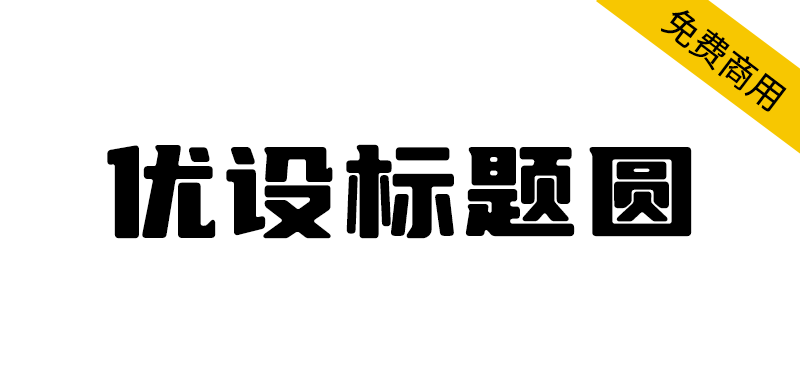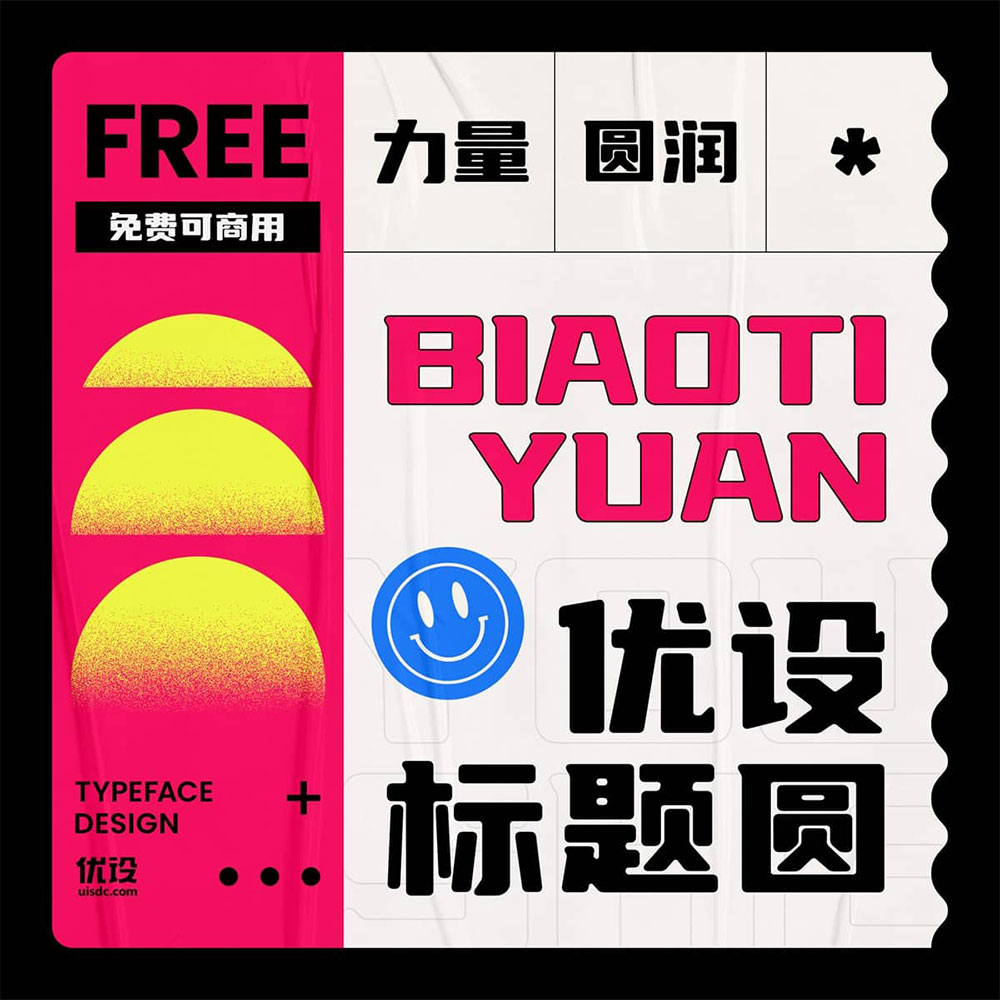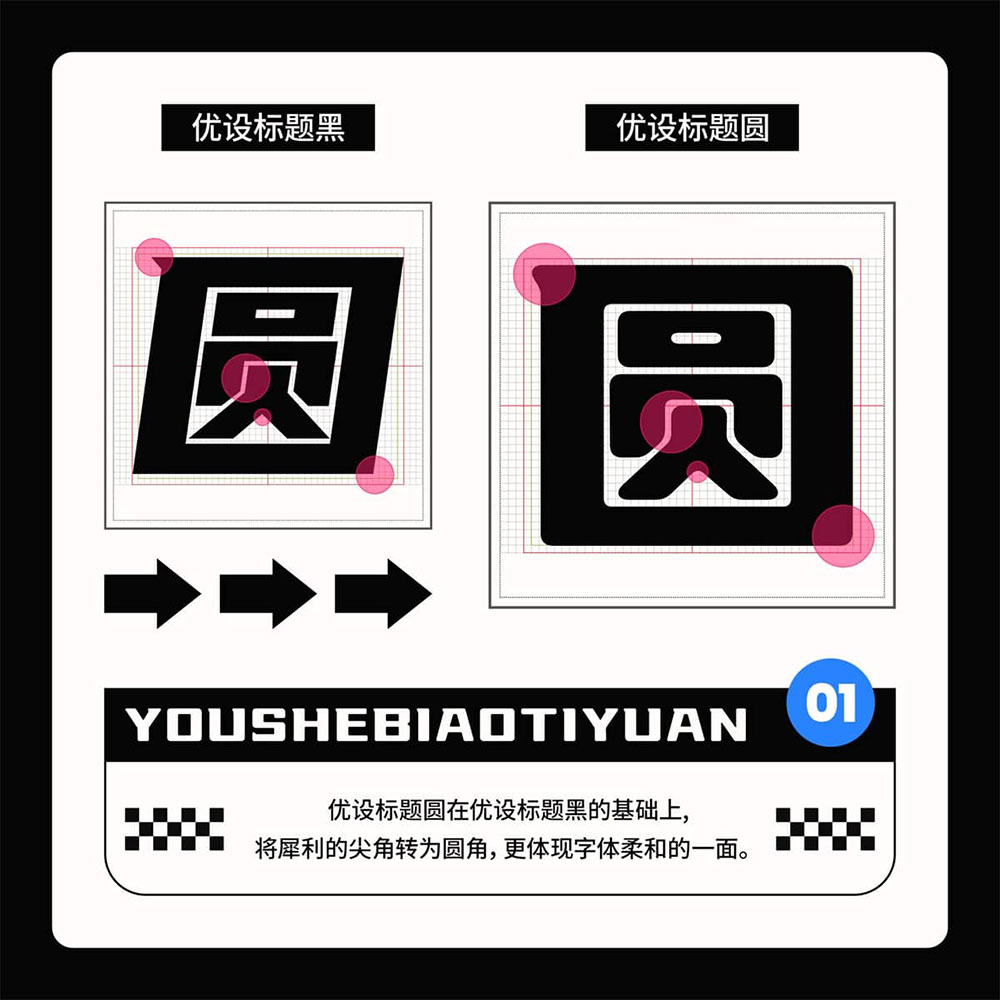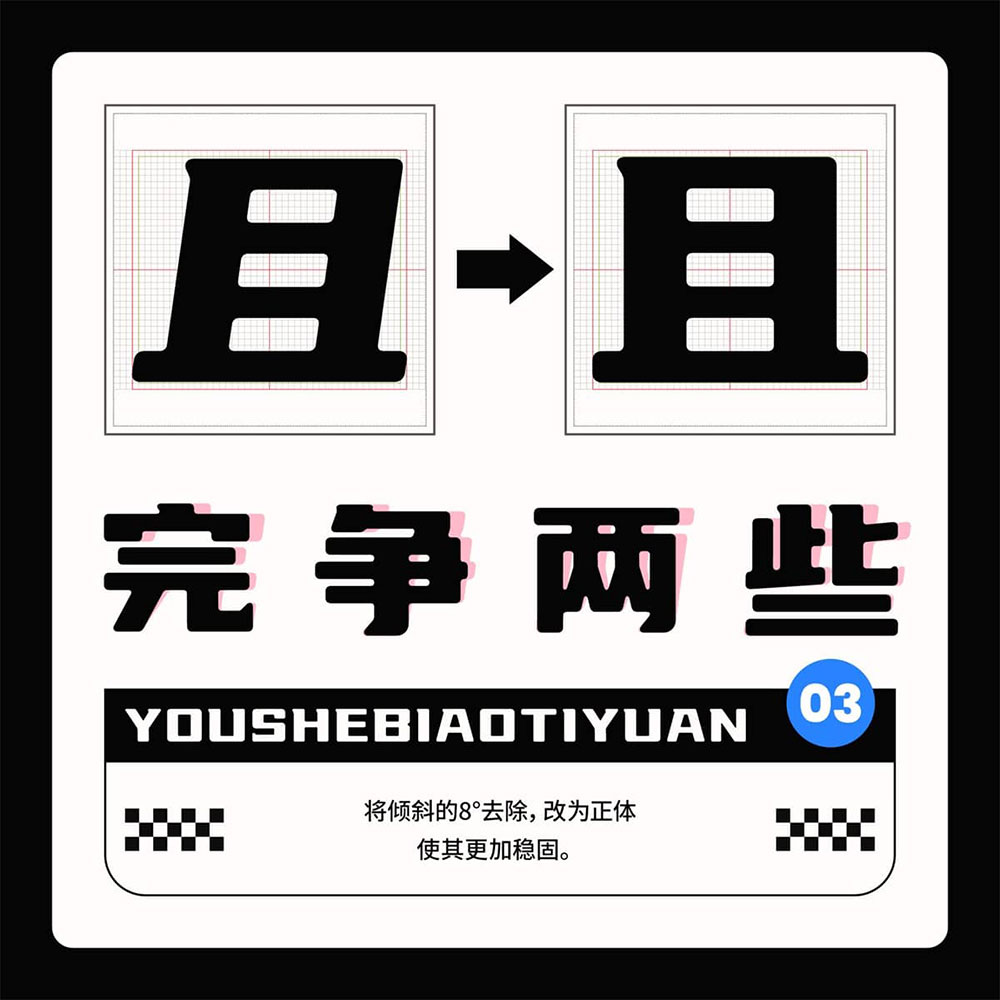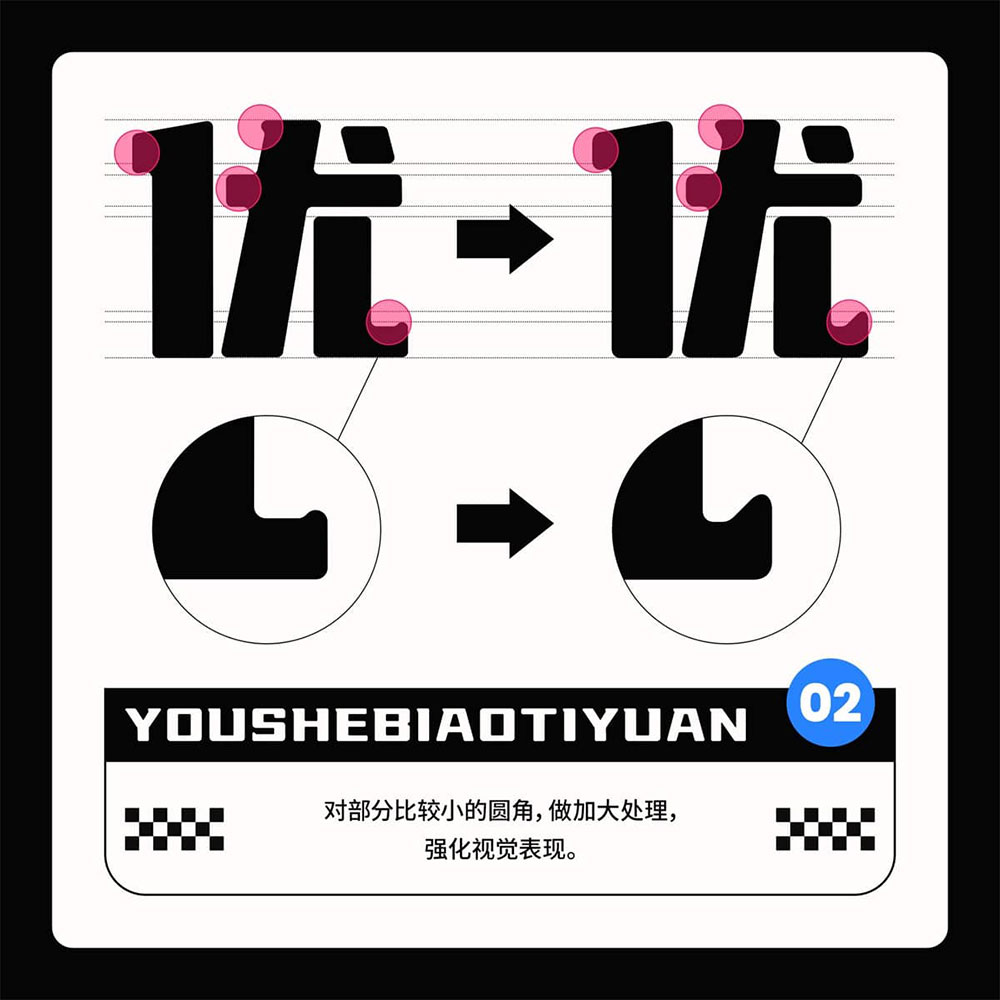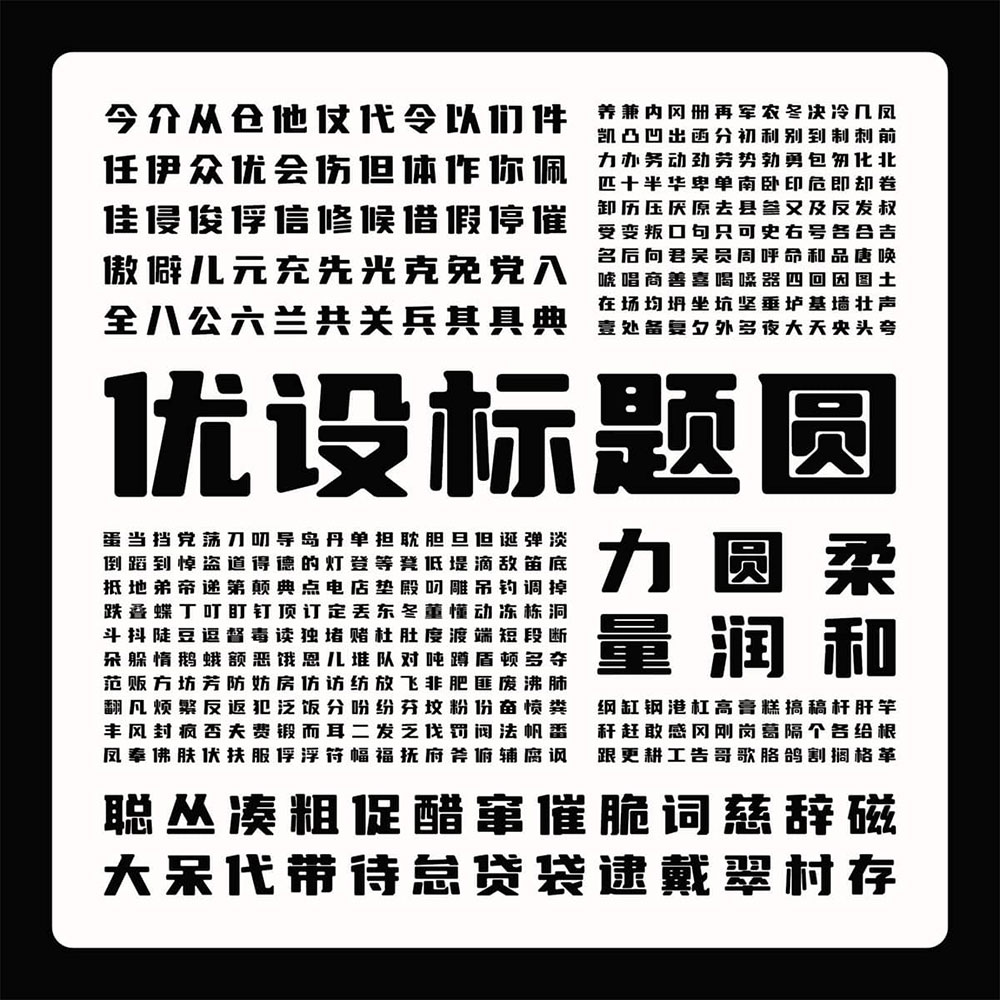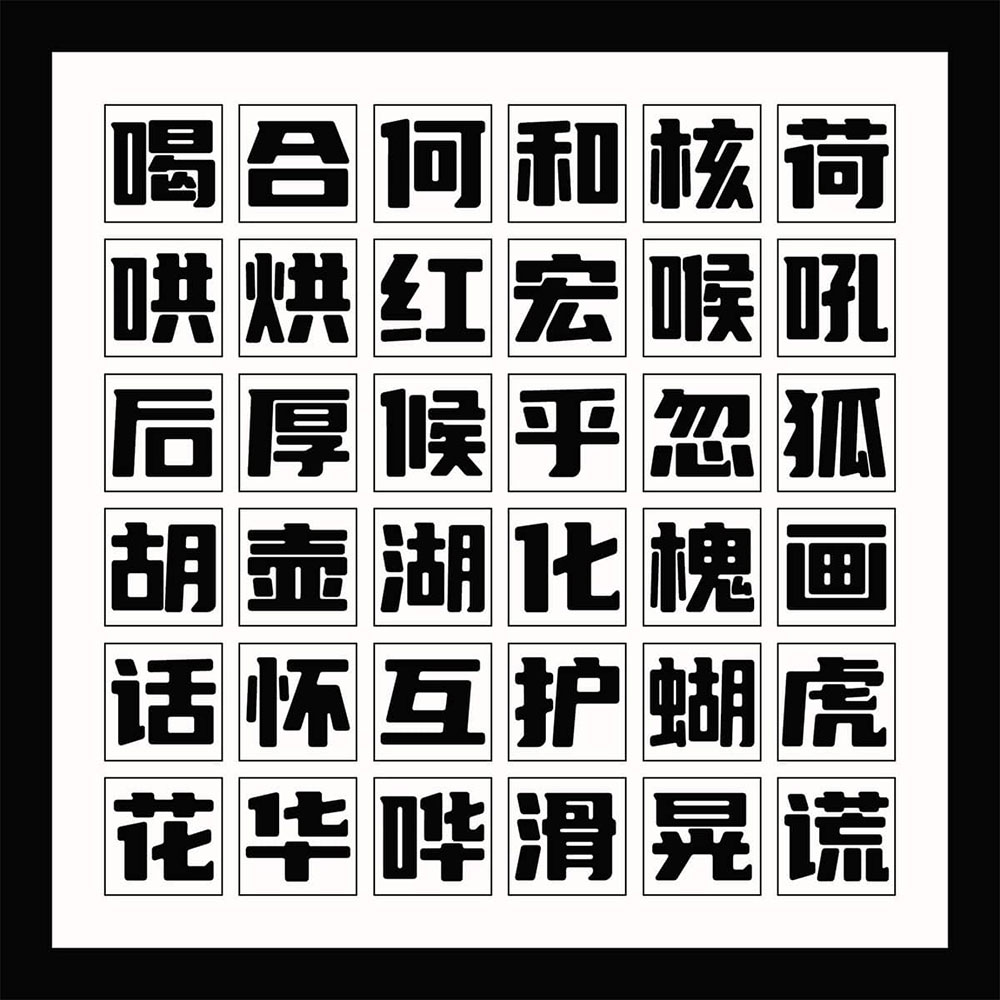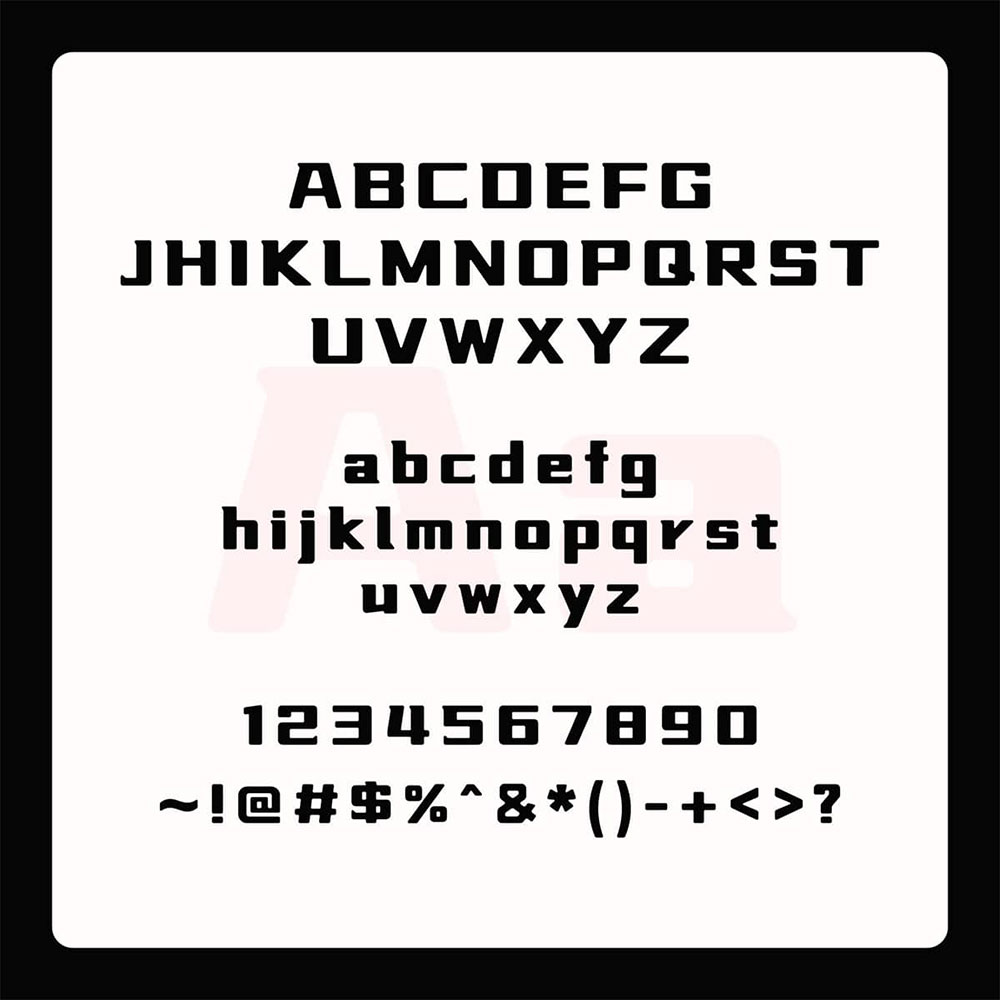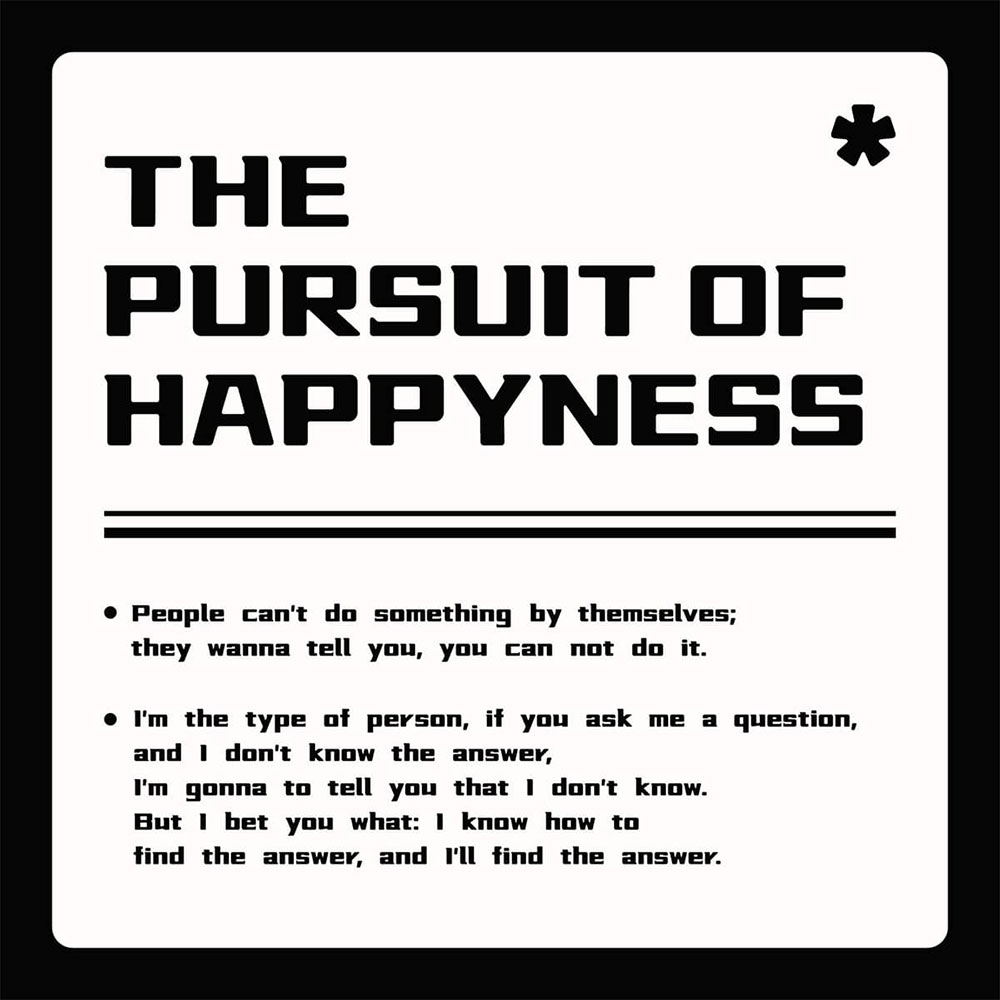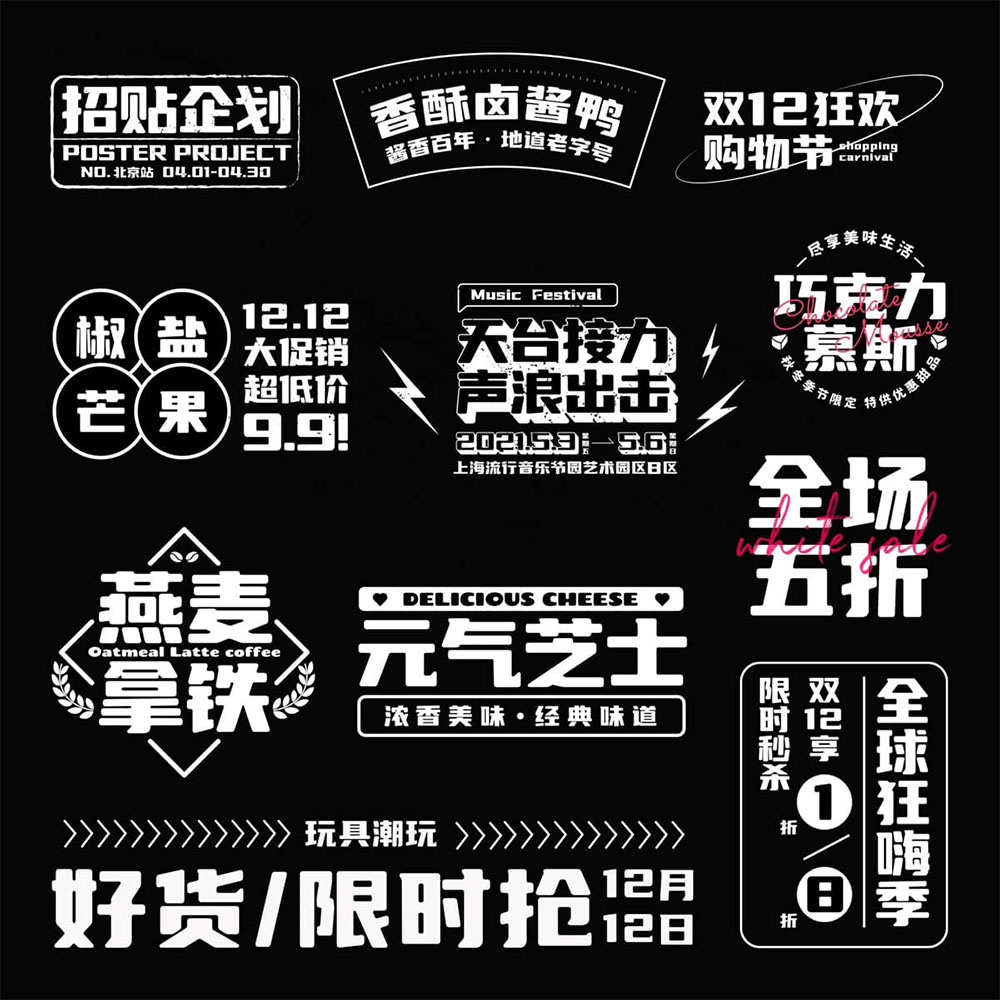
【优设标题圆】优设标题黑的升级版,从斜体变为正体
优设标题圆作为「优设标题黑」的兄弟版,这款字体在保留「优设标题黑」的力量感的基础上,将8°倾斜去除,从斜体变为正体,减弱速度感,增加稳固的感受,同时将尖角改为圆角,让其更适用于温和的宣传广告和产品包装设计,字体整体风格与标题黑形成直接对比,一个刚毅,一个柔和。